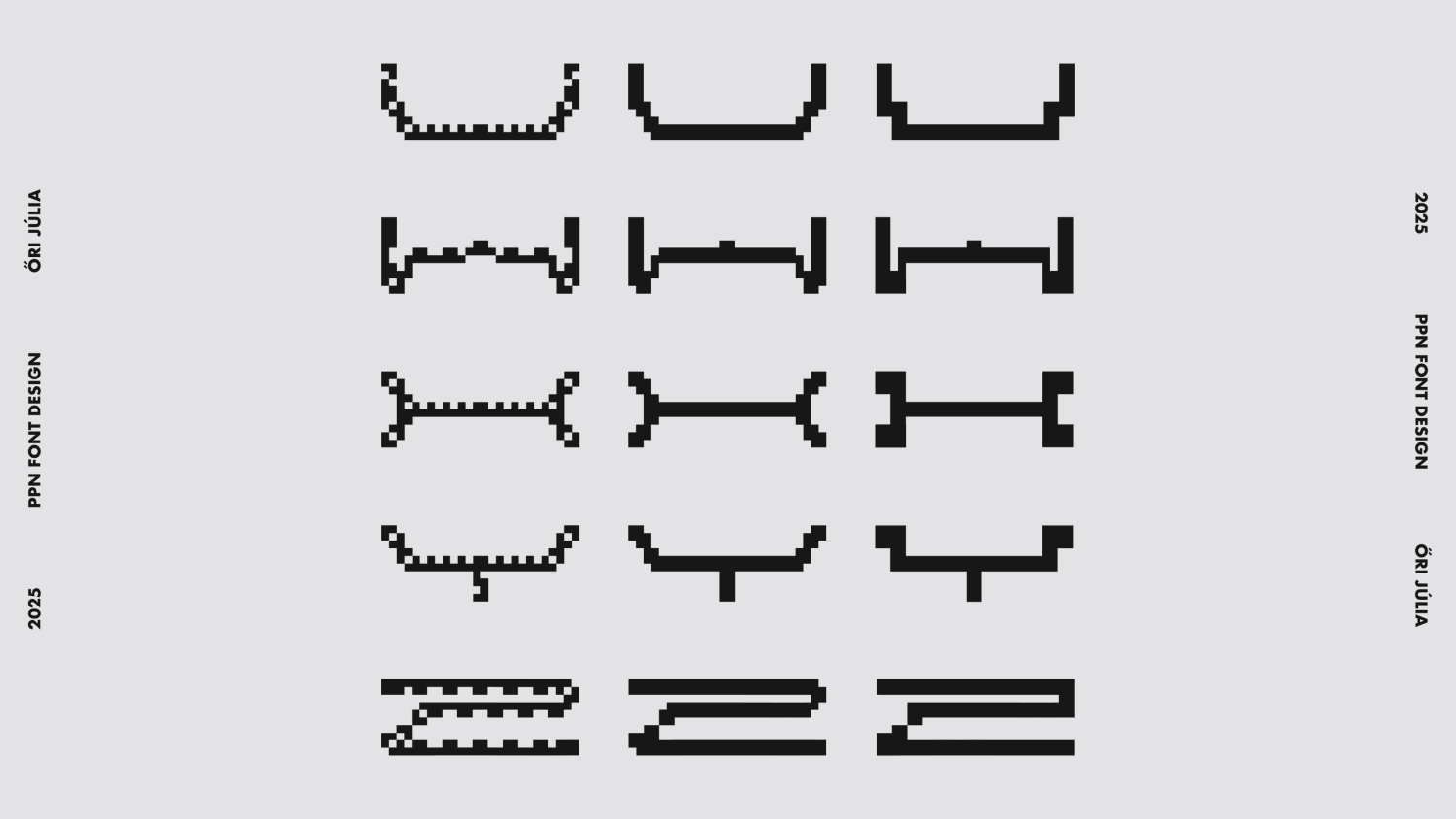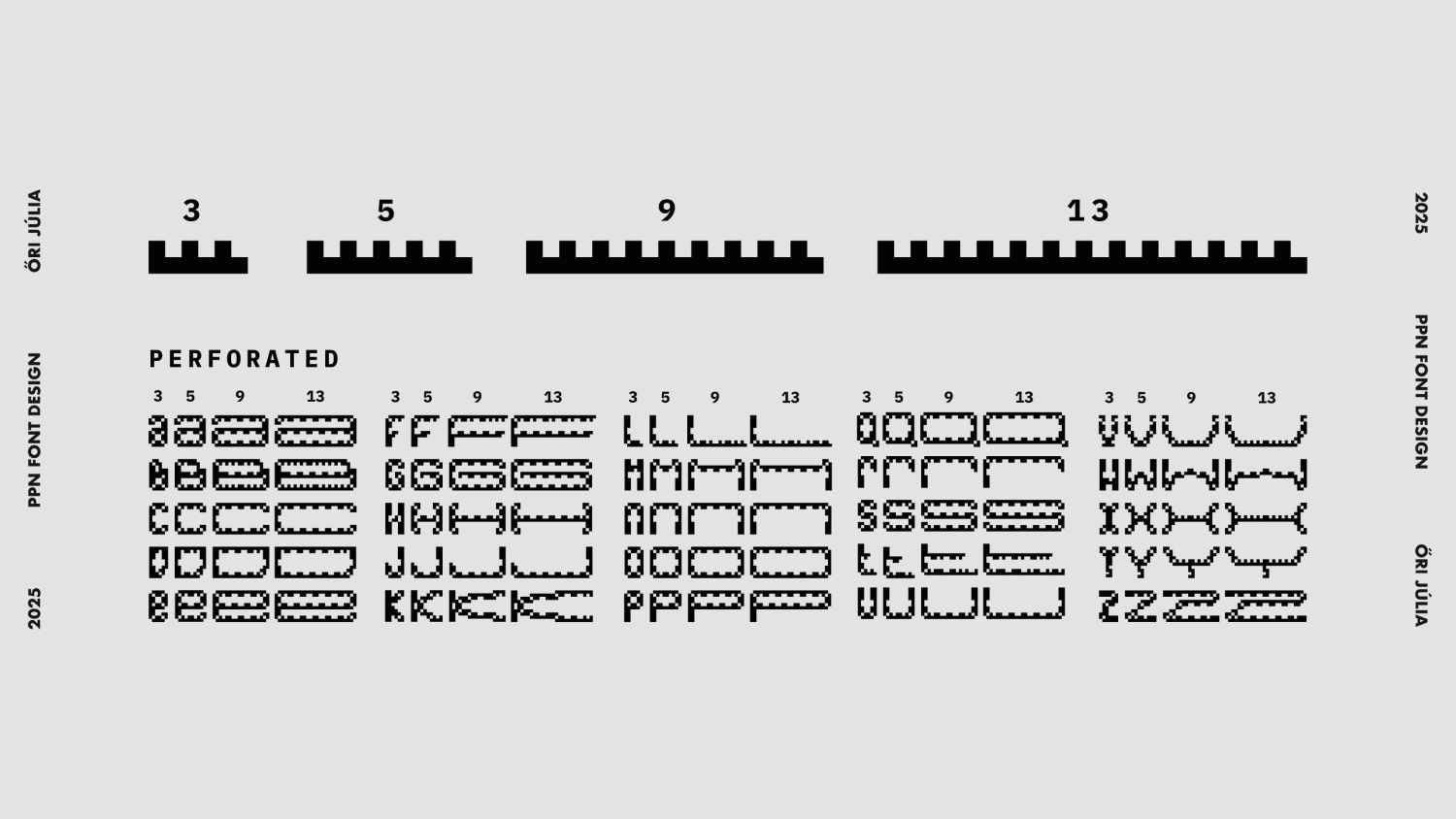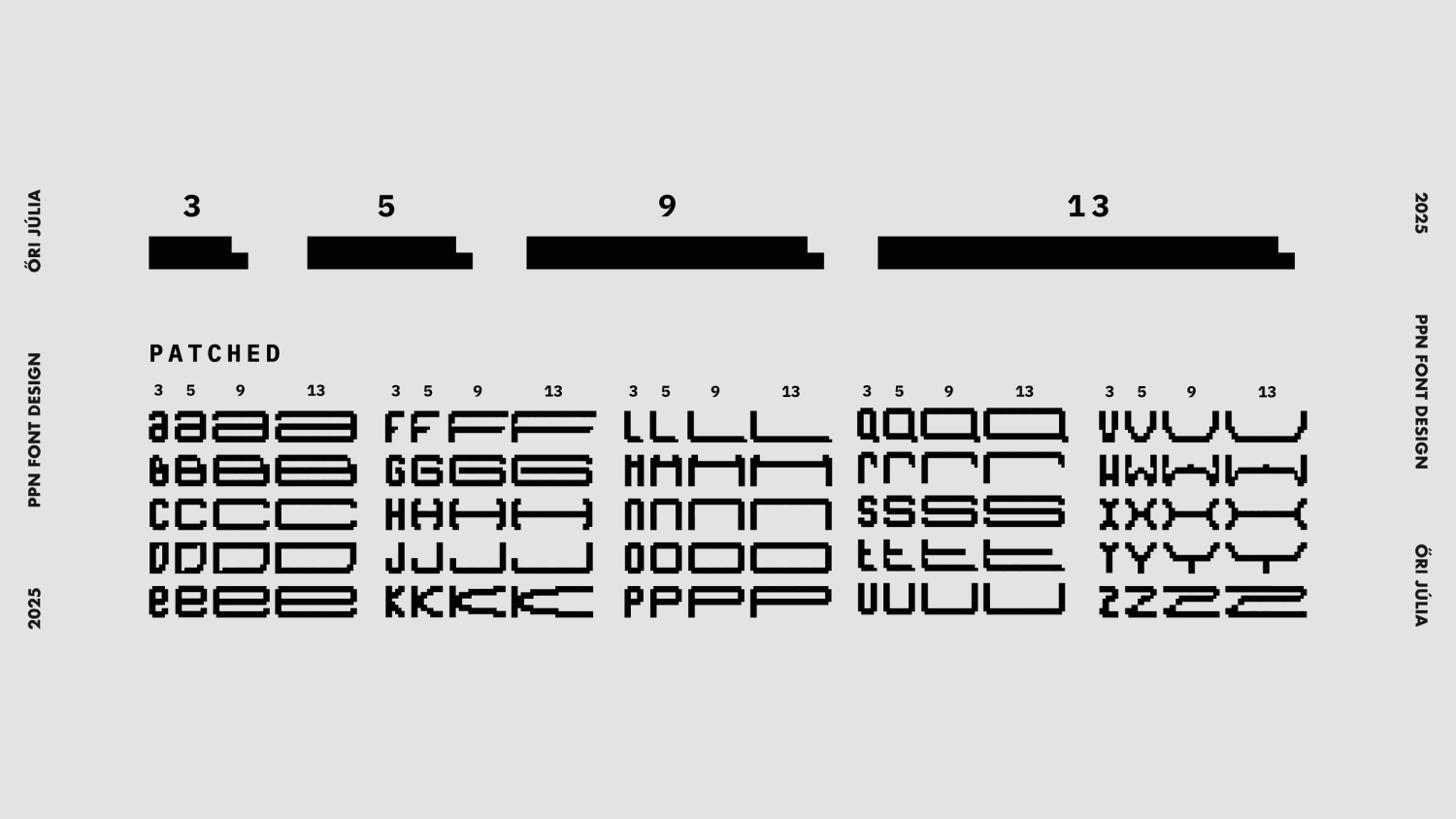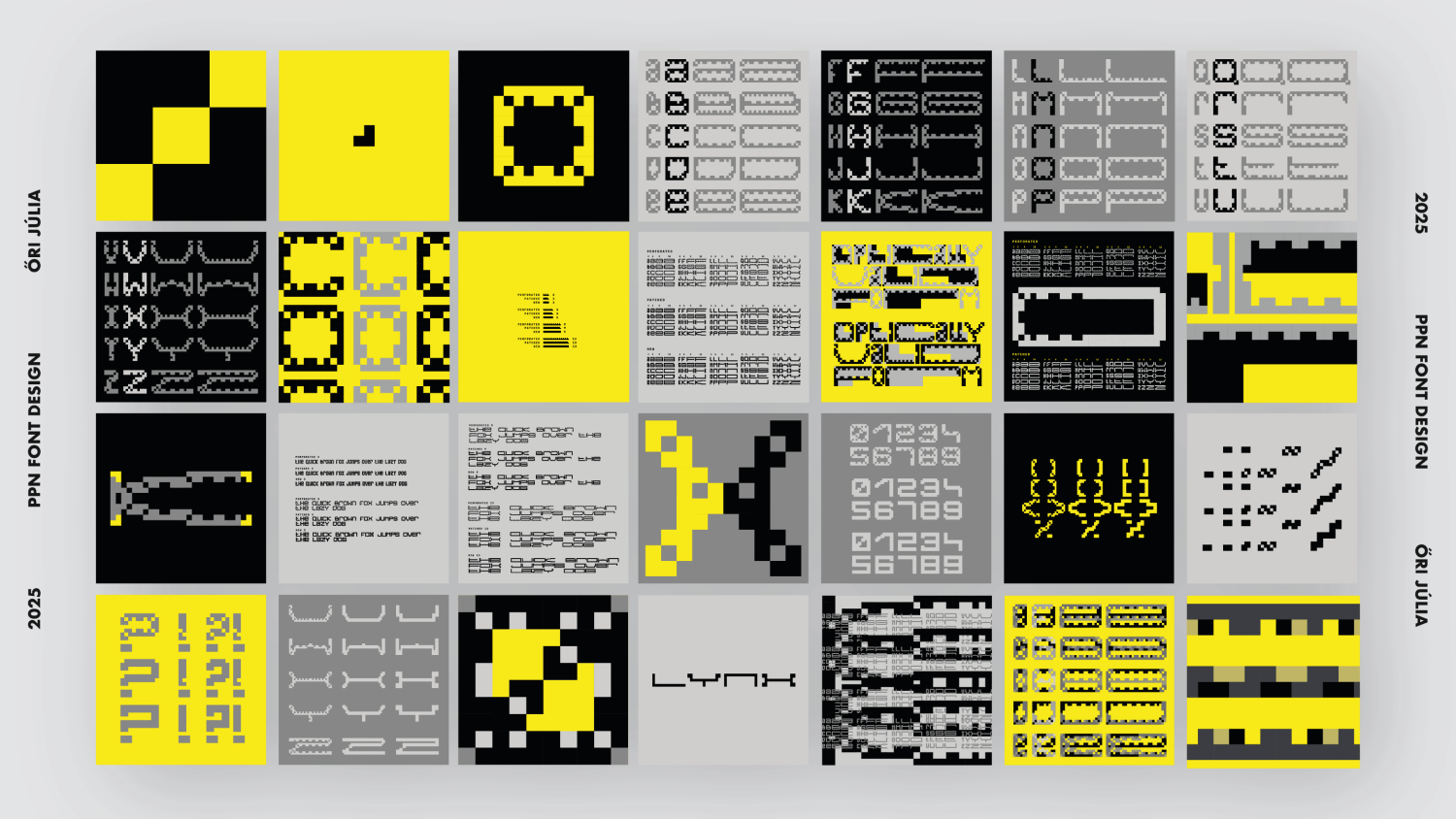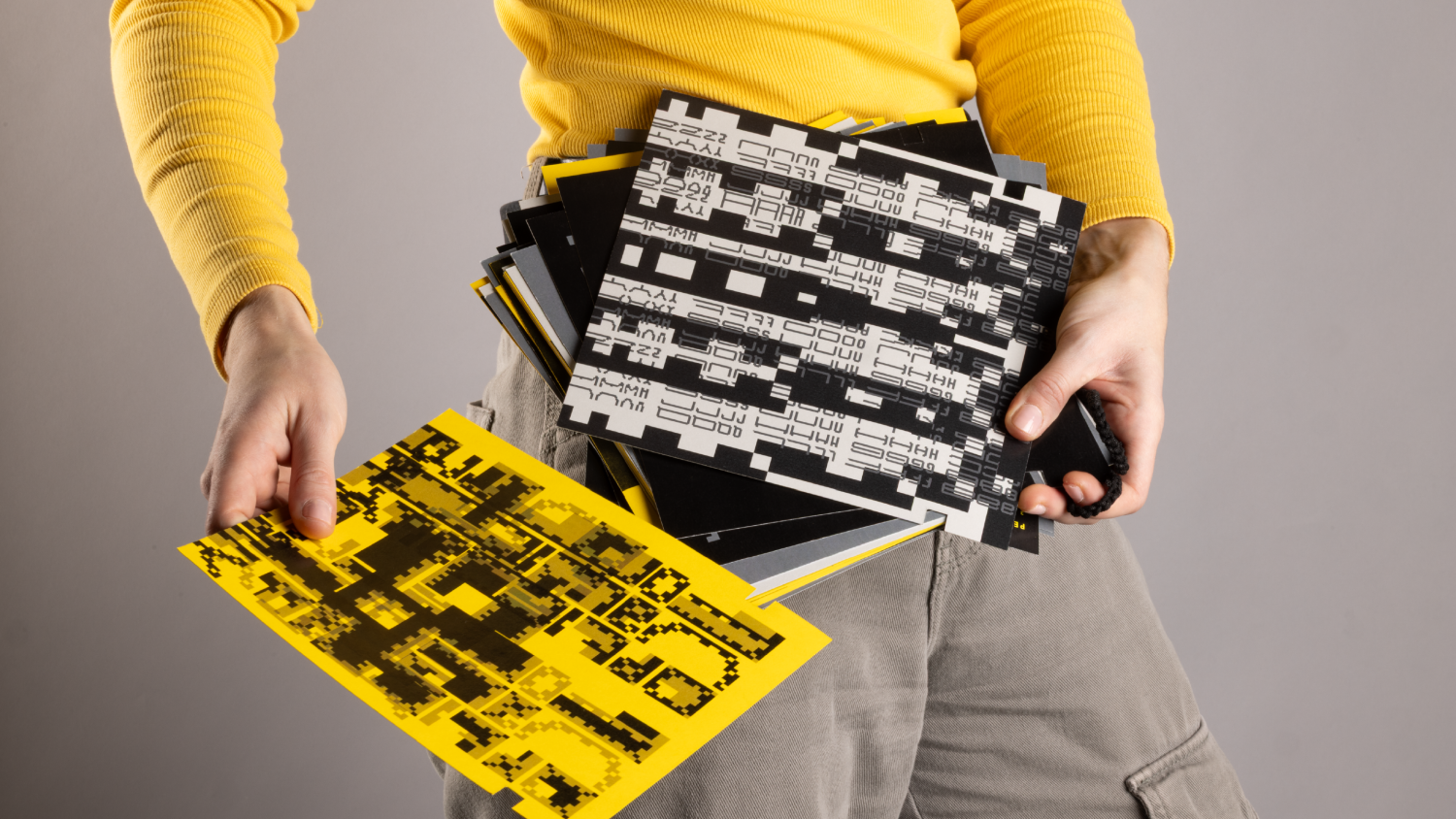
PPN Font Design
A PPN (Perforated, Patched, New) betűtípust az annak alaprendszerét alkotó sarokelem végtelen nyújhatósága jegyében terveztem. A 3 vastagság az elem által okozott hézagok fokozatos befoltozásával változik: Perforated (lyukacsos, perforált), Patched (foltozott) és New (új).